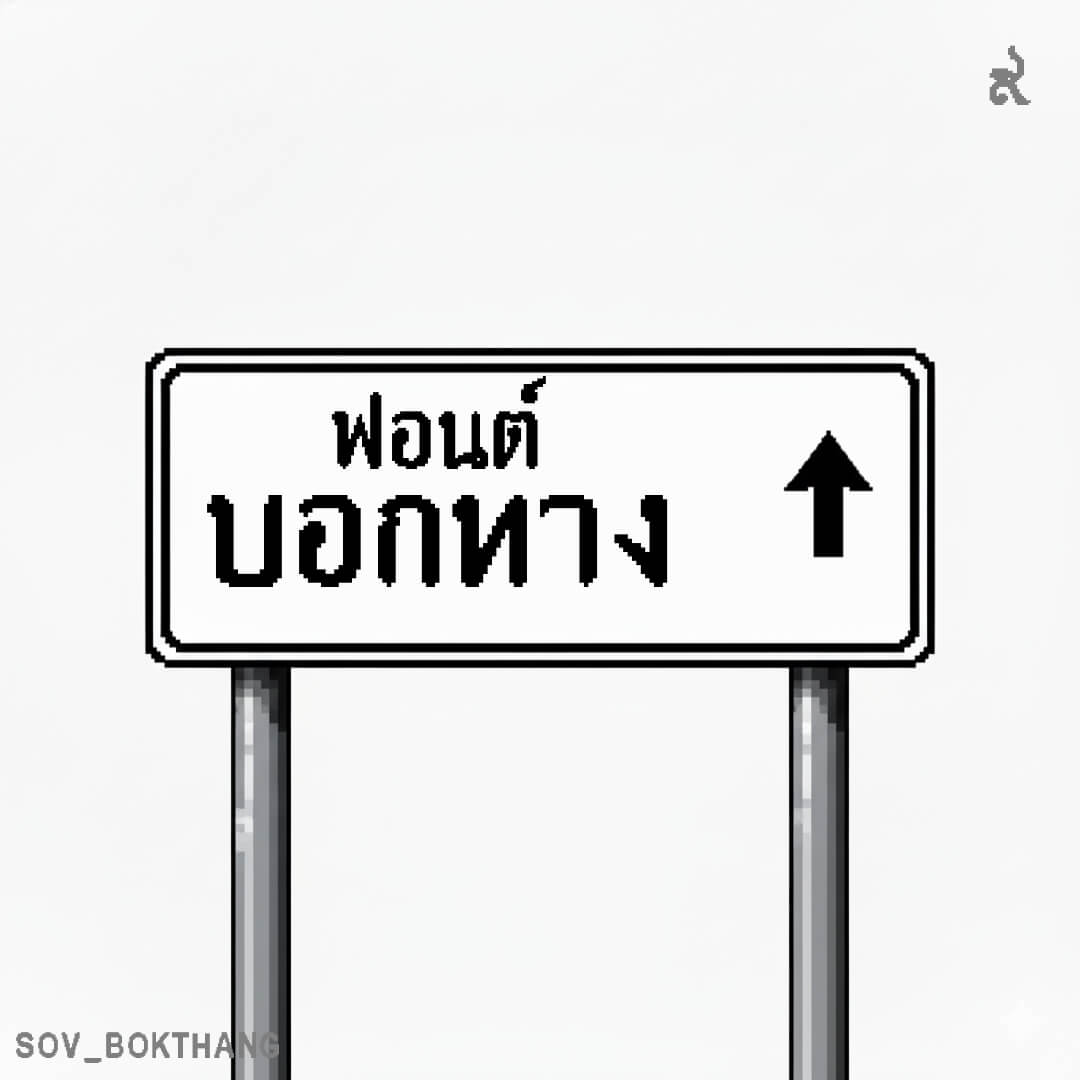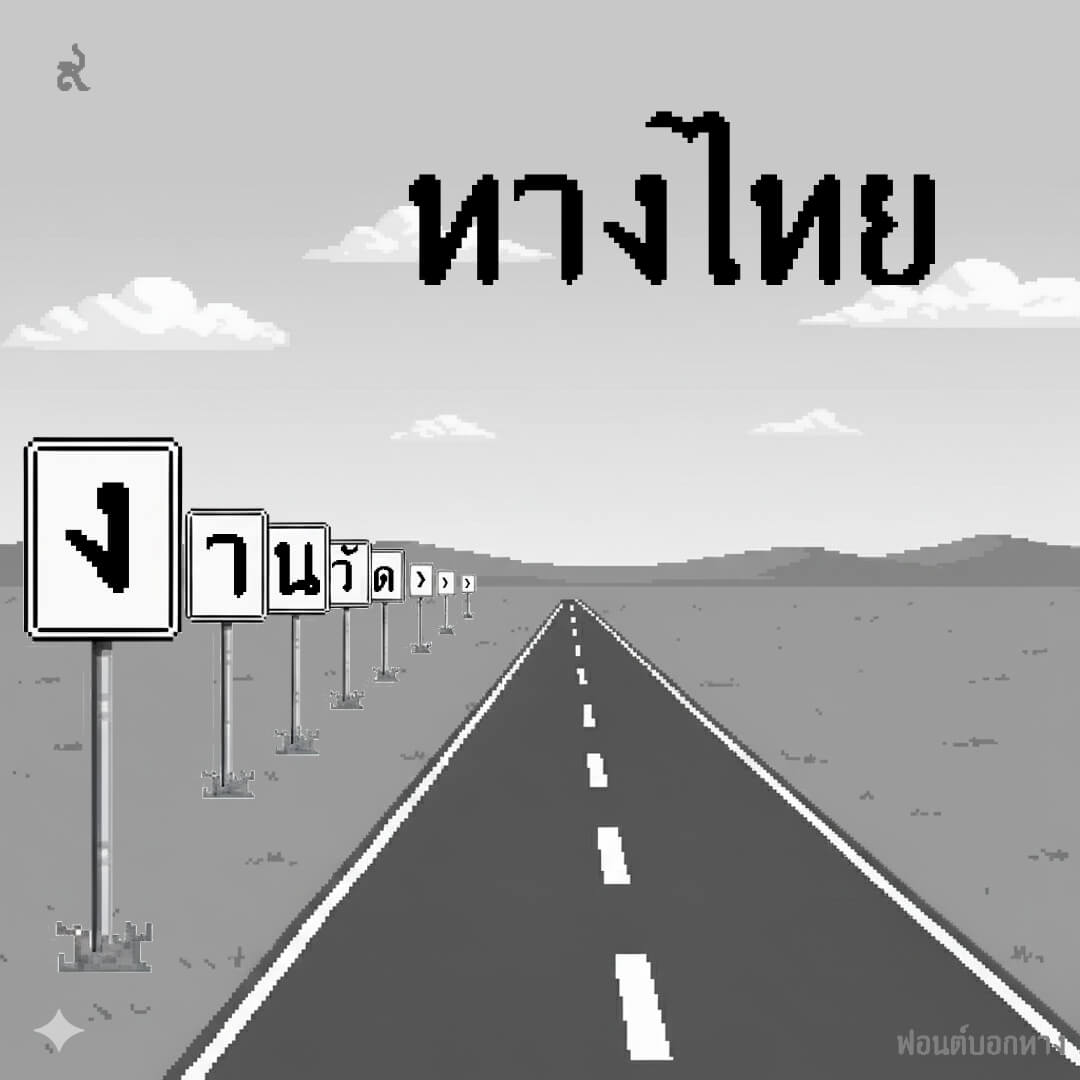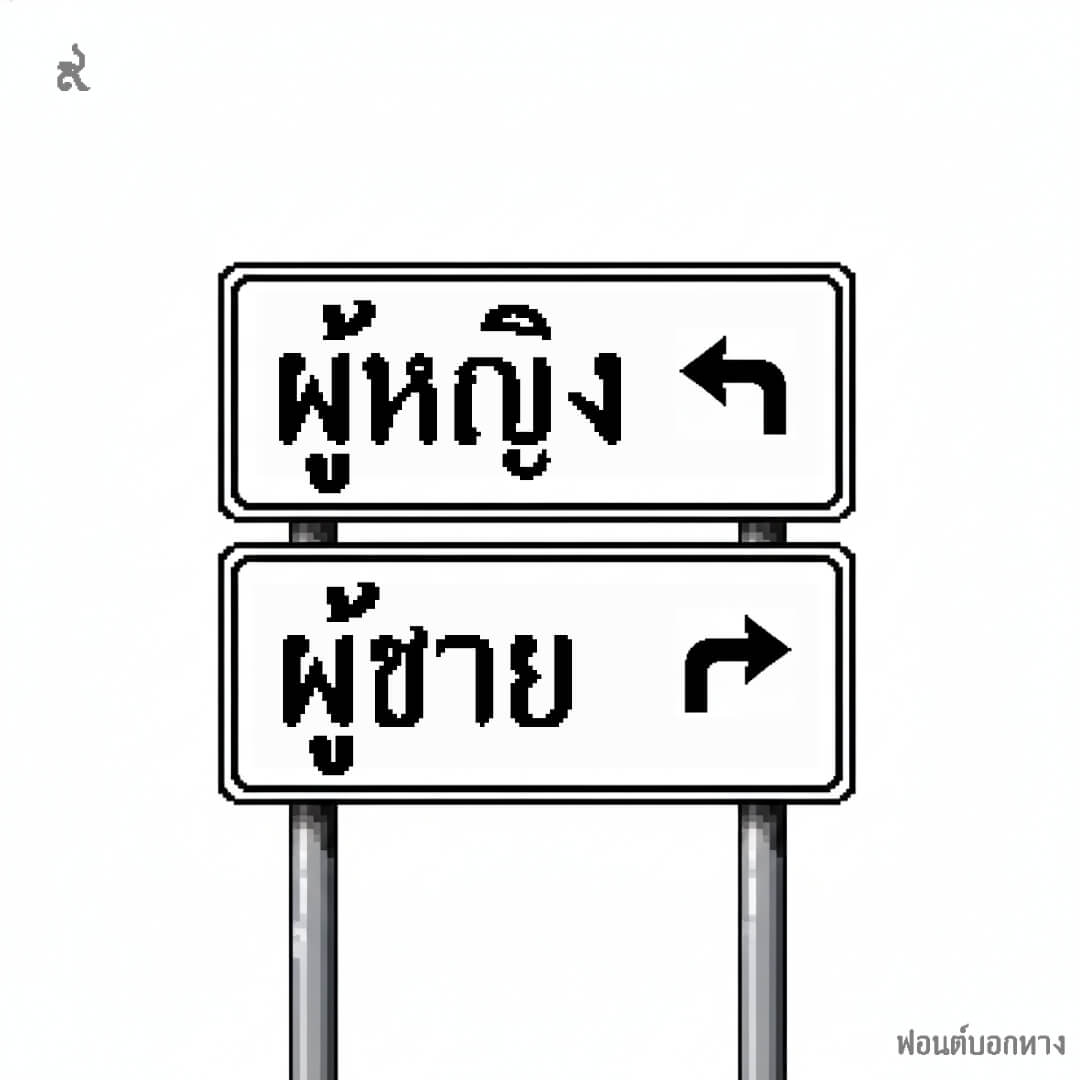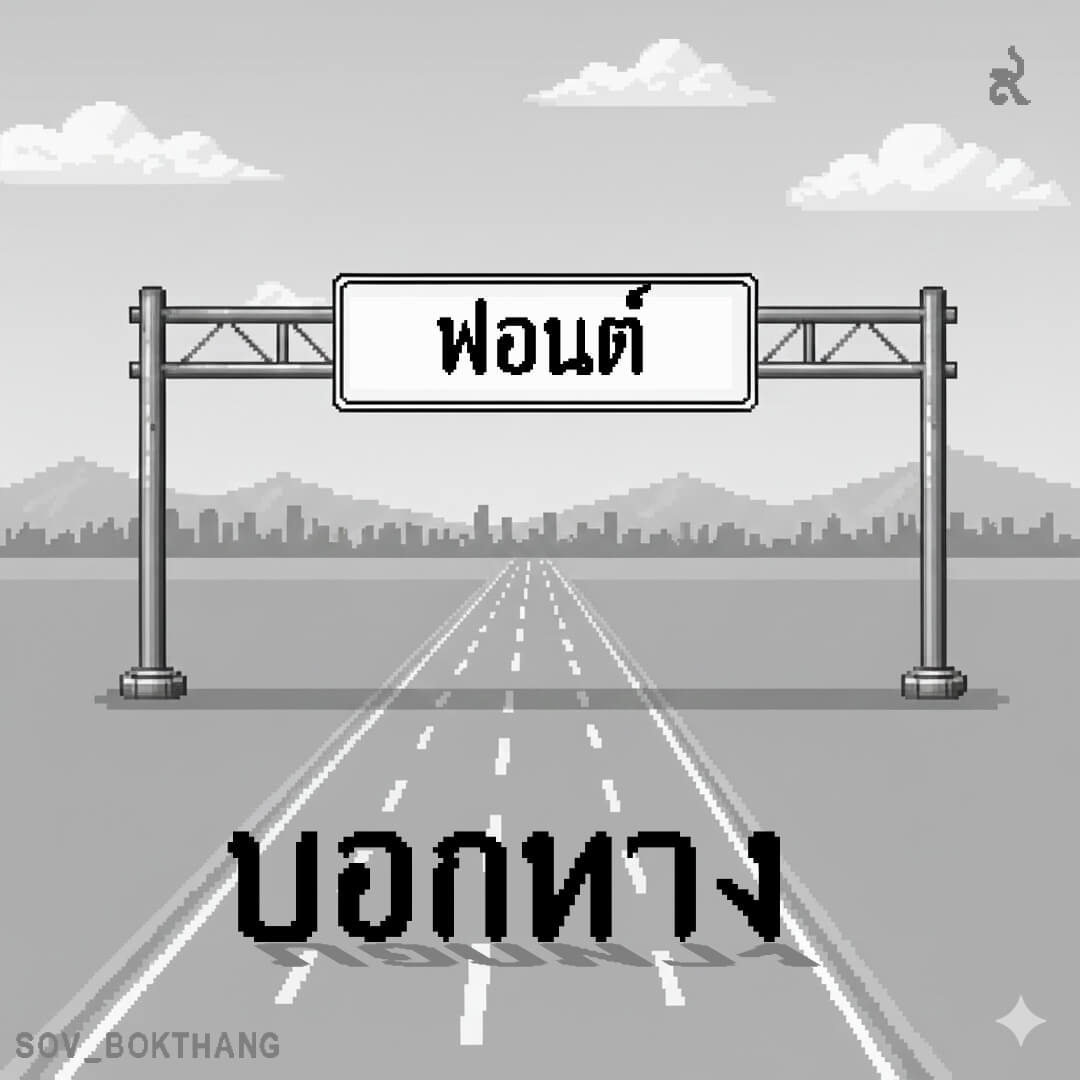
บอกทาง – เอาฟอนต์ป้ายทางหลวง มาทำเป็น 8-bit pixel art …เผื่อสายสถาปัตย์ 8 bit เอาไว้ใช้ในการขยายถนน เชื่อมเมือง
เบื้องหลังการออกแบบ : ฟอนต์ บอกทาง
บอกทาง (SOV_BokThang)